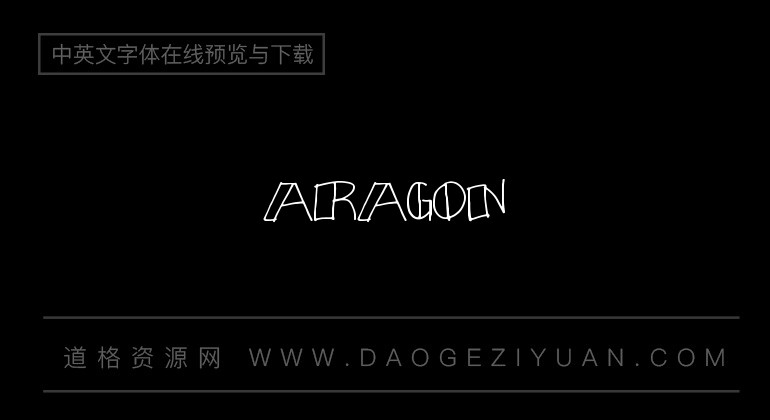
Aragon 字体是由 Monotype Imaging Inc. 公司设计的一款字体。它是一种现代西班牙风格的字体,具有清晰的外观,较大的字体大小,以及优雅的线条。它可以用于各种文档,包括出版物,广告,标签,标题,网页等。Aragon 字体的特点是它有一种独特的西班牙风格,让它的字体看起来非常优雅。它还可以让您的文档更加引人注目,为您的项目增添一丝活力。内容介绍
Aragon是一款非常不错的手写艺术字体,具有很好的视觉感,适合于文化类的宣传设计、商业类品牌的广告和产品包装设计以及个性化文字排版等较多场景。